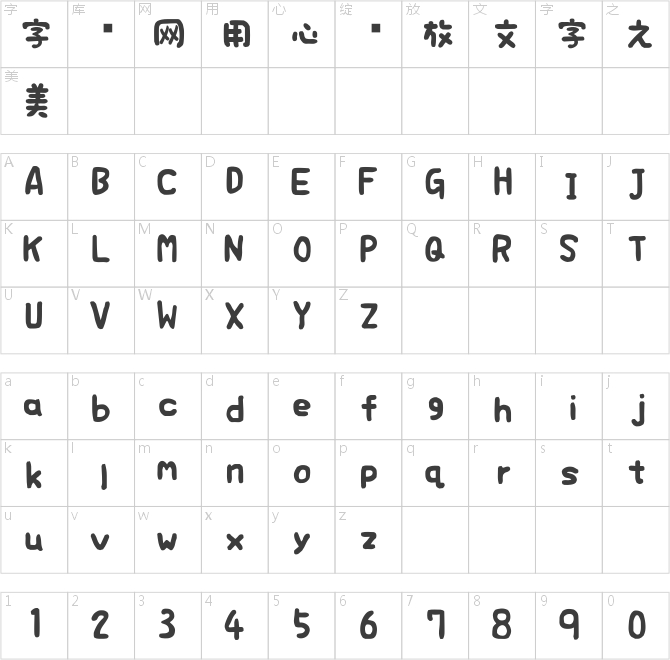
字體名稱: 豆豆字體えるま
豆豆字體えるまー
豆豆字體えるまー介紹
えるまーフォント<等幅> ver.1.60
えるまーPフォント<プロポーショナル> ver1.60
マジックペンで書いたような手書きフォントです。<第二水準まで>
足跡やハート等が罫線の後半に入っています?!袱堡い护蟆工驂鋼Qさせてみてください。